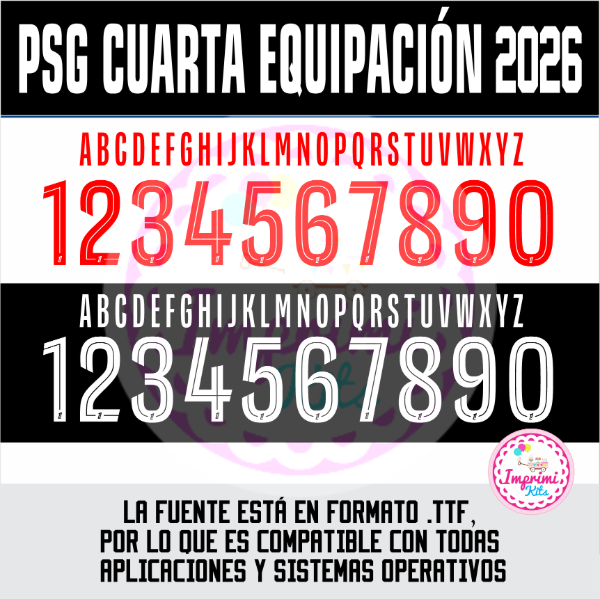
Tipografia PSG 2026 Cuarta Equipación Camiseta Ttf Otf Numeros Dorsal
Tipografía Números Fuente
Realizá todo tipo de creaciones con la tipografía utilizada actualmente en el club